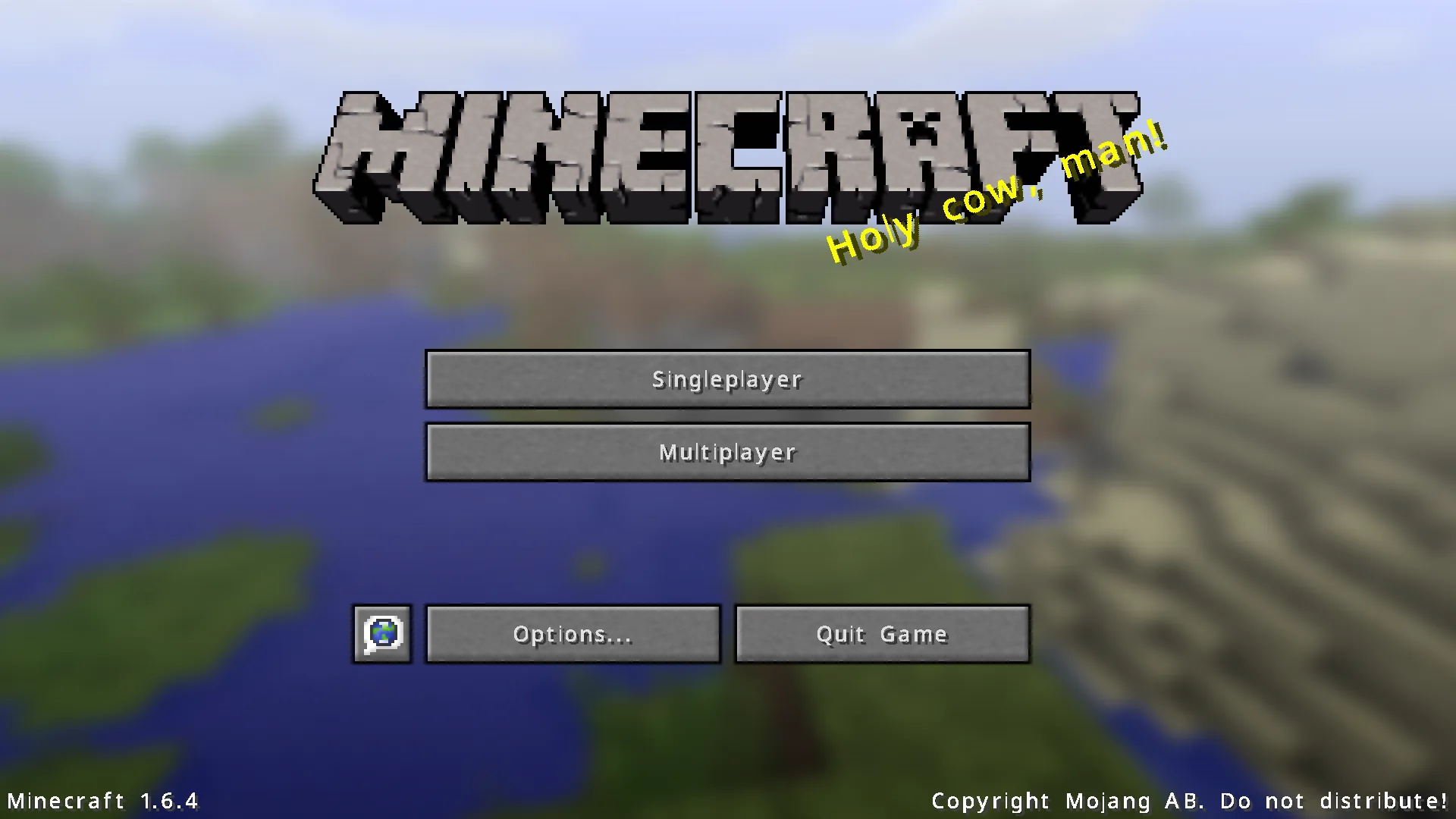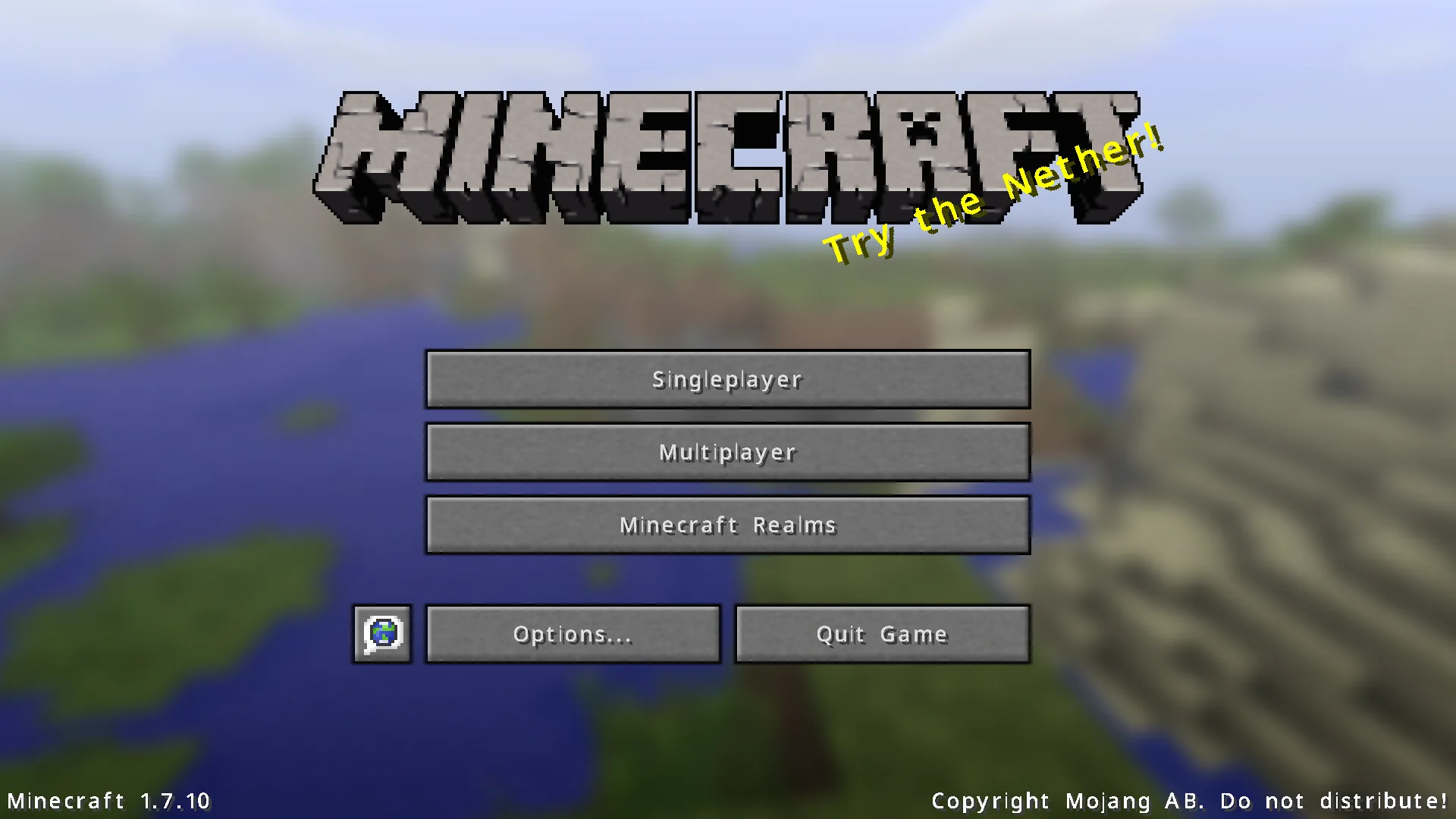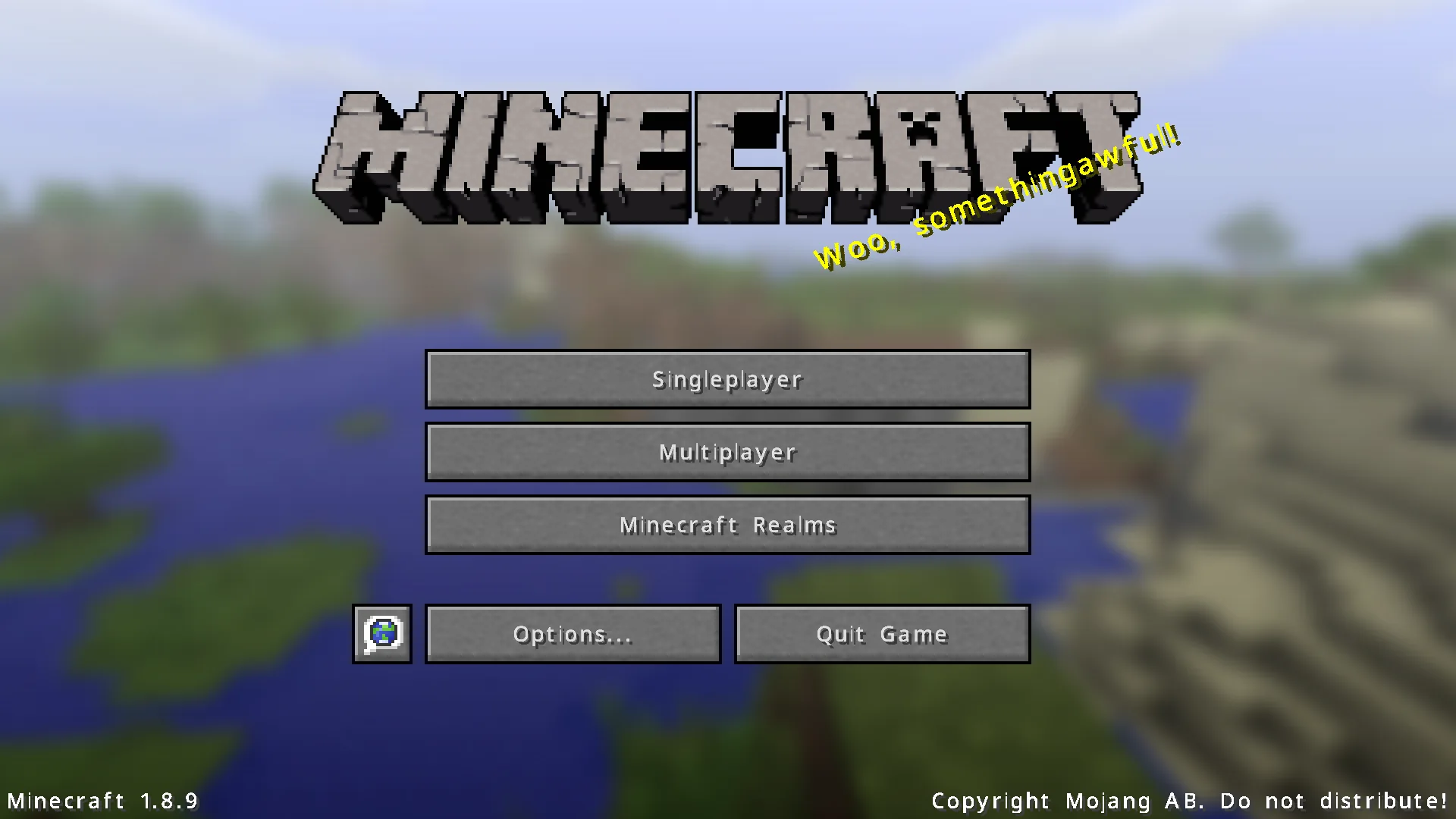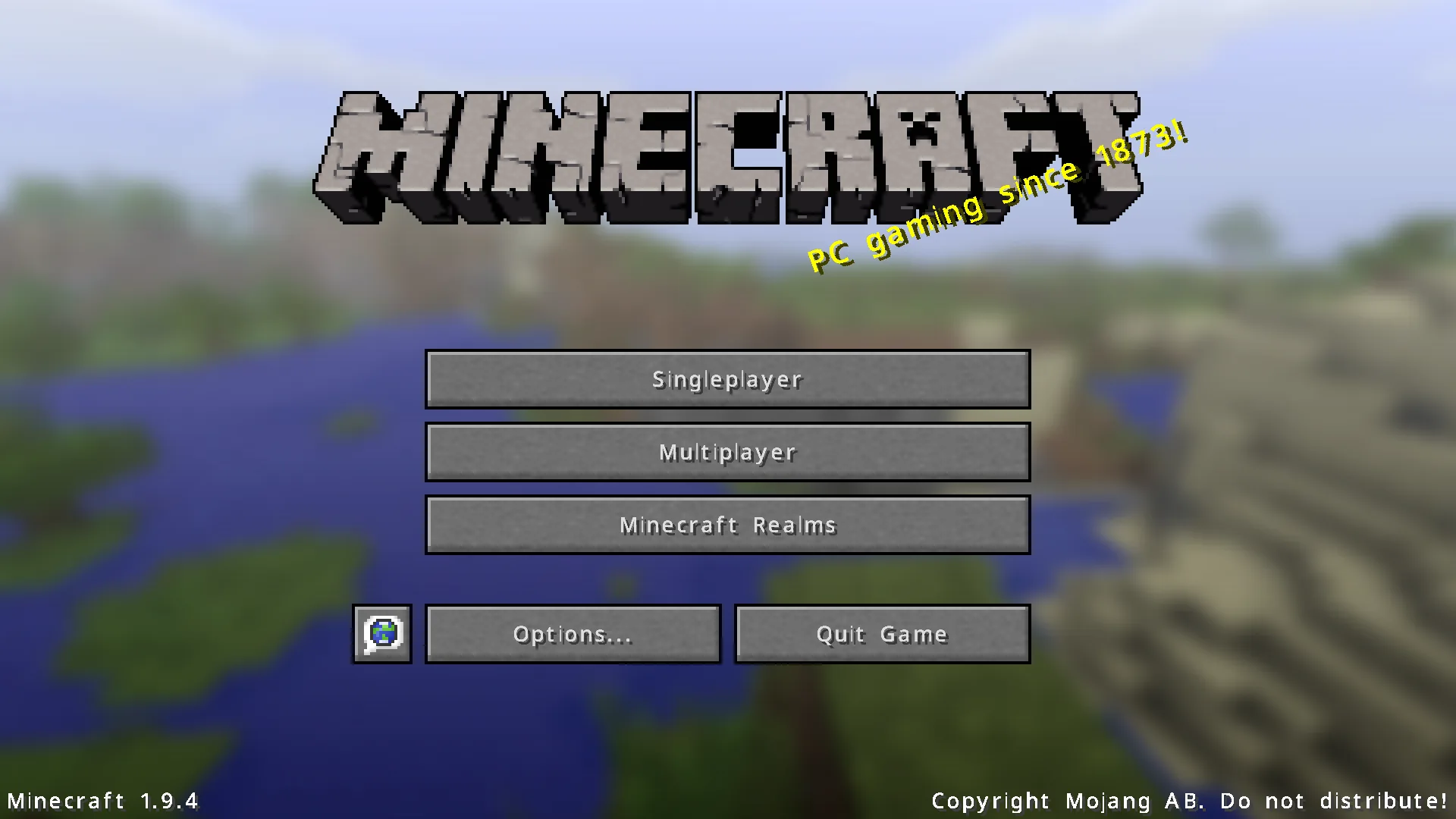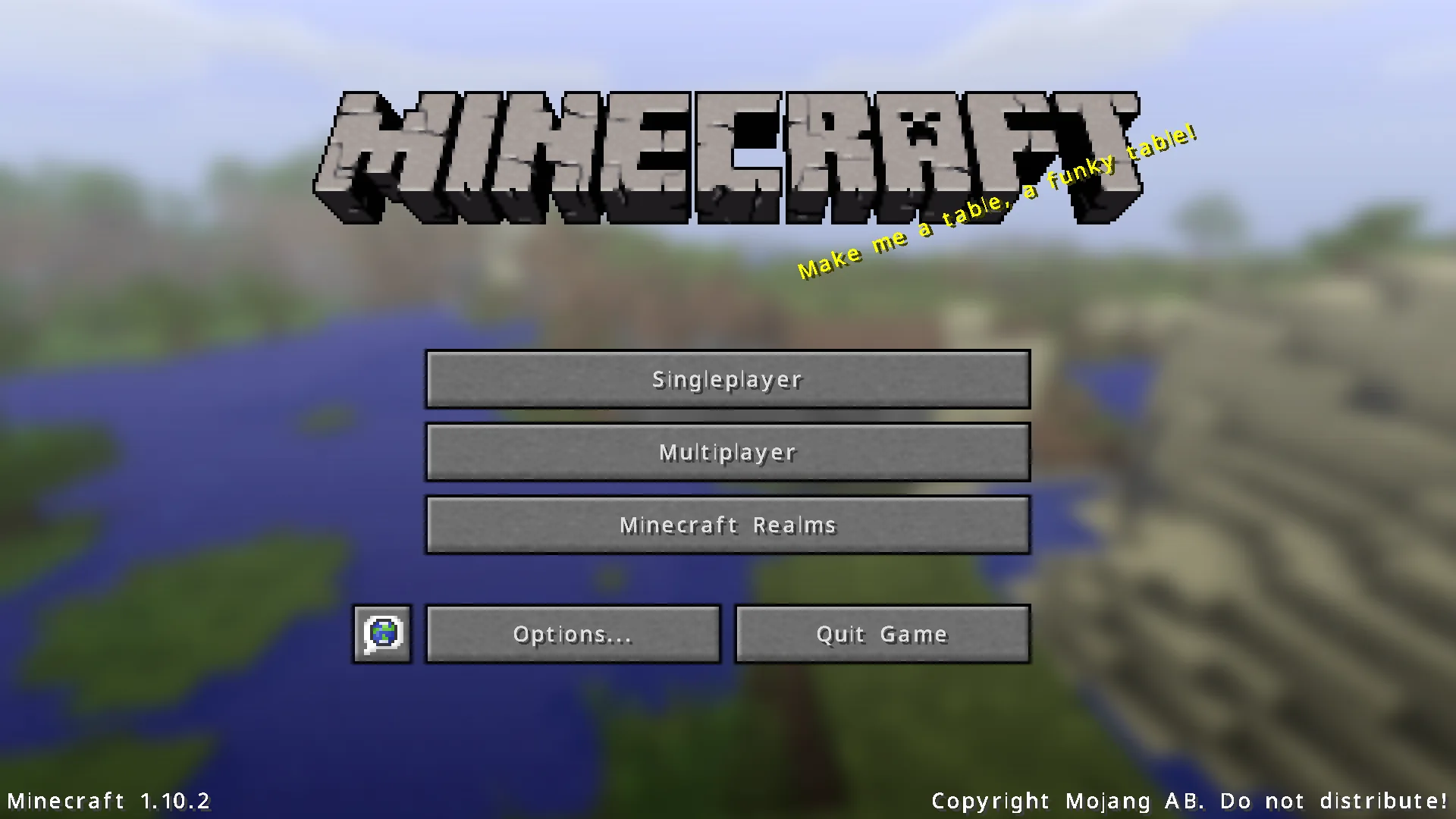
Modern Font Pack
Ресурспак модернизирует шрифт Minecraft, делая его гладким и красивым. Доступны три версии с разными уровнями сглаживания для различных разрешений экрана.
Этот ресурспак заменяет стандартный толстый и крупный шрифт Minecraft на современный и гладкий, что особенно заметно на экранах с высоким разрешением. Он решает проблему грубого отображения текста даже при включённой опции Force Unicode Font.
Доступны три основные версии: HD Version, Basic Version и Supreme Version. Каждая версия включает пять вариантов для разных языковых регионов (JP, KR, CN, TW, HK), использующих шрифты семейства Noto Sans от Google. HD Version предназначена для стандартного использования, Basic Version использует базовое сглаживание для экранов с низким разрешением, а Supreme Version обеспечивает максимальную гладкость для разрешений QHD и 4K UHD.
Ресурспак также поддерживает эмодзи и специальные символы, взятые из семейств шрифтов Noto Emoji, Noto Sans Math и Noto Sans Symbols. Это позволяет использовать их непосредственно в игре.